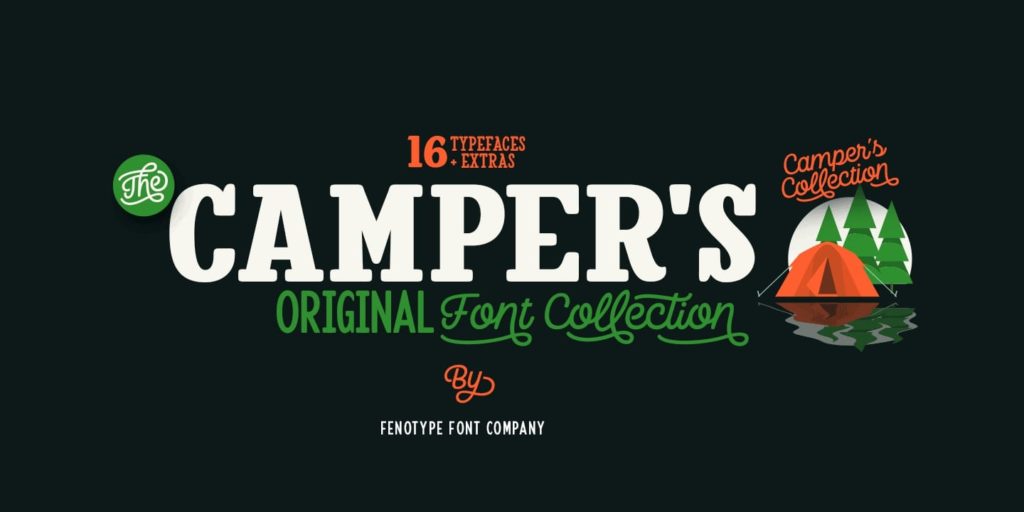
Шрифт Camper
Шрифт Camper — это обширное декоративное семейство от финского дизайнера Emil Karl Bertell, выпущенное словолитней Fenotype. Гарнитура включает в себя 22 стиля, среди которых — скриптовые, рубленые, брусковые и декоративные шрифты, а также набор дополнительных элементов . Основой коллекции является связный (connected) скрипт с низким контрастом и тремя весами. Особенностью всех шрифтов семейства является широкая языковая поддержка, включая кириллицу, что делает их отличным выбором для проектов на русском языке, где требуется выразительный и неформальный стиль. Оцените возможности семейства, и если вы ищете универсальный декоративный набор для самых разных задач, вы можете ознакомиться с ним на этой странице.